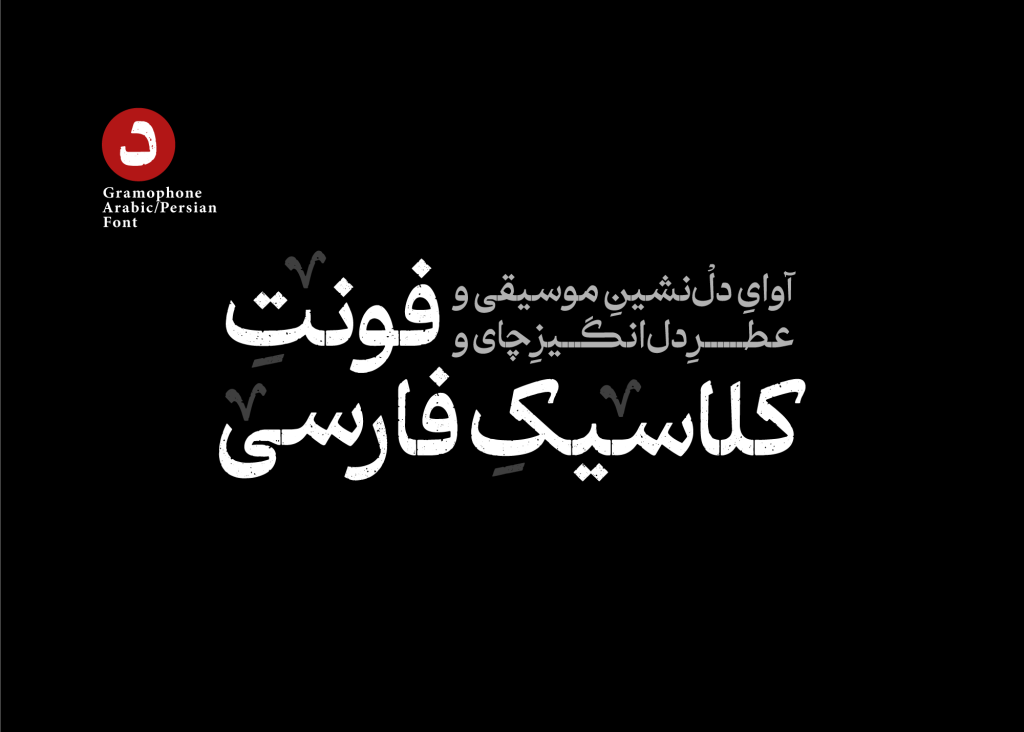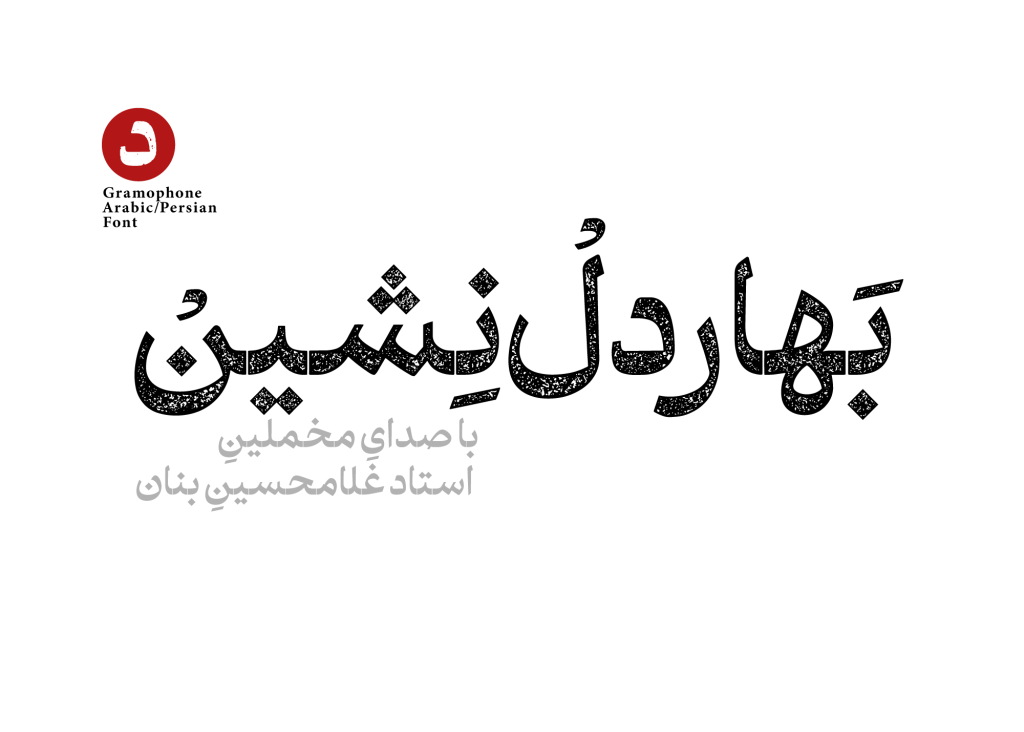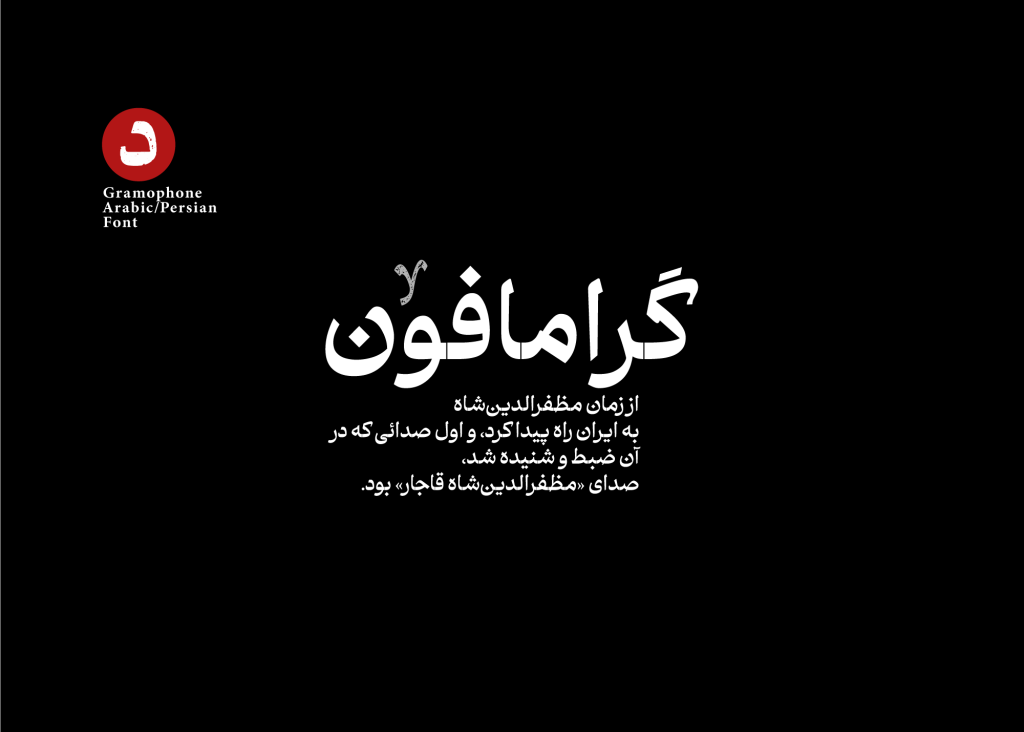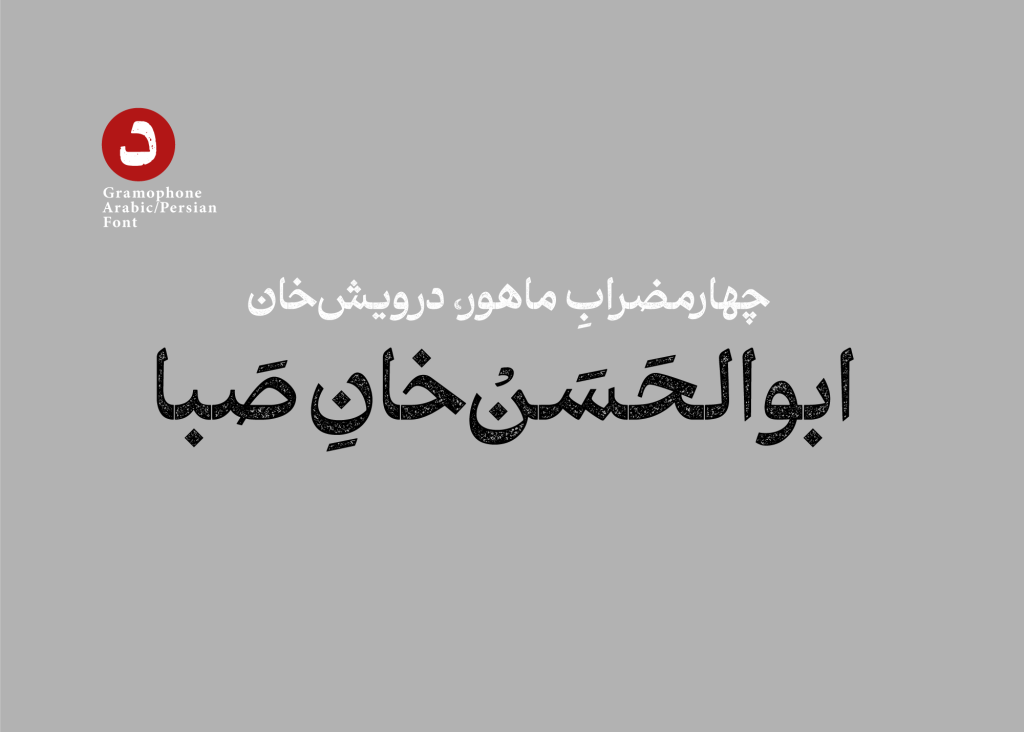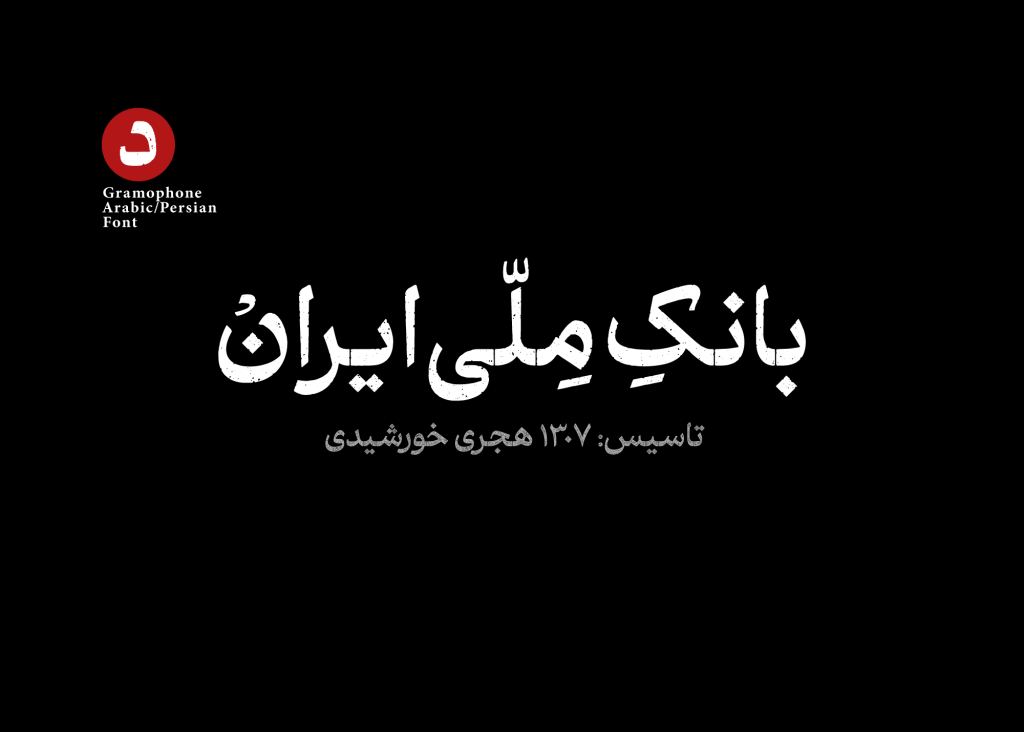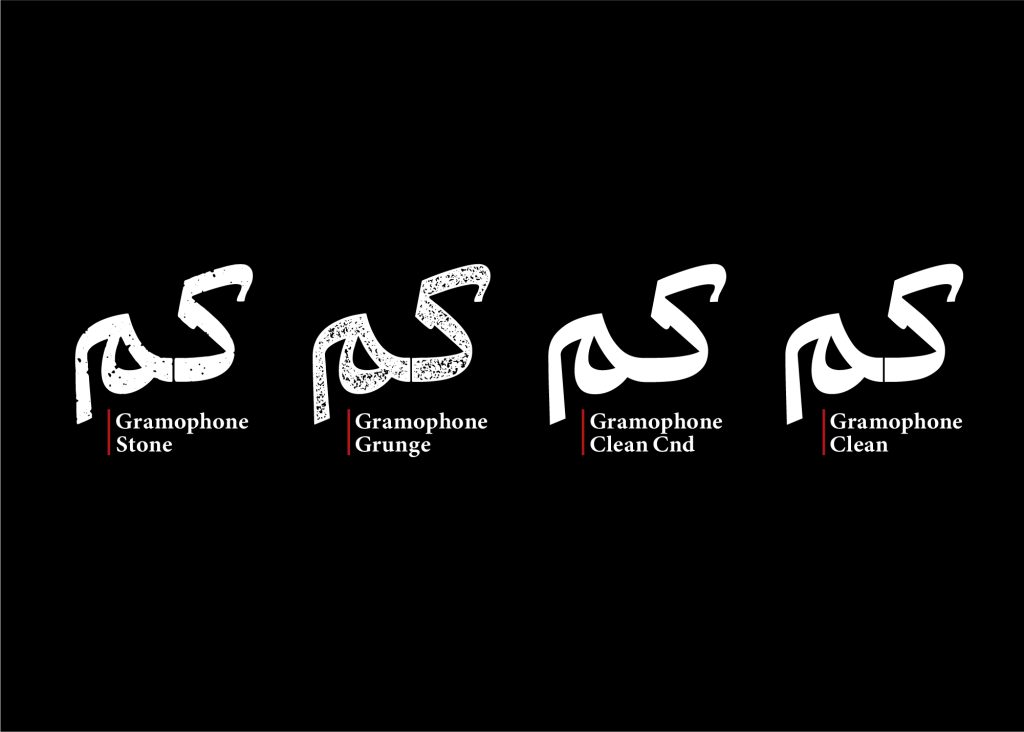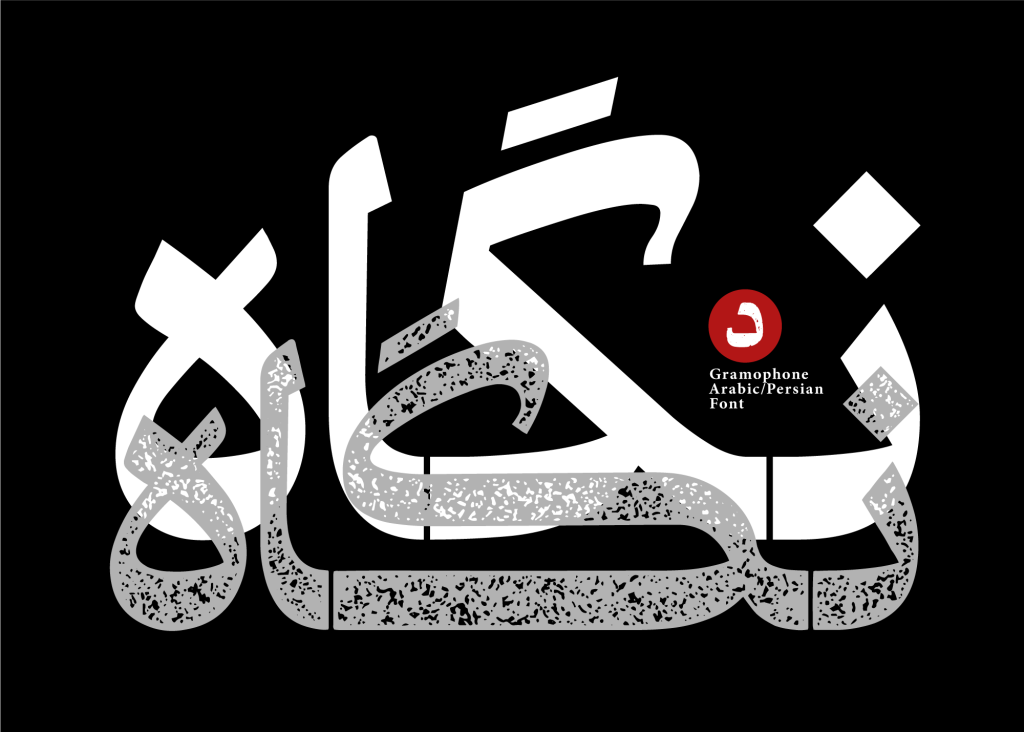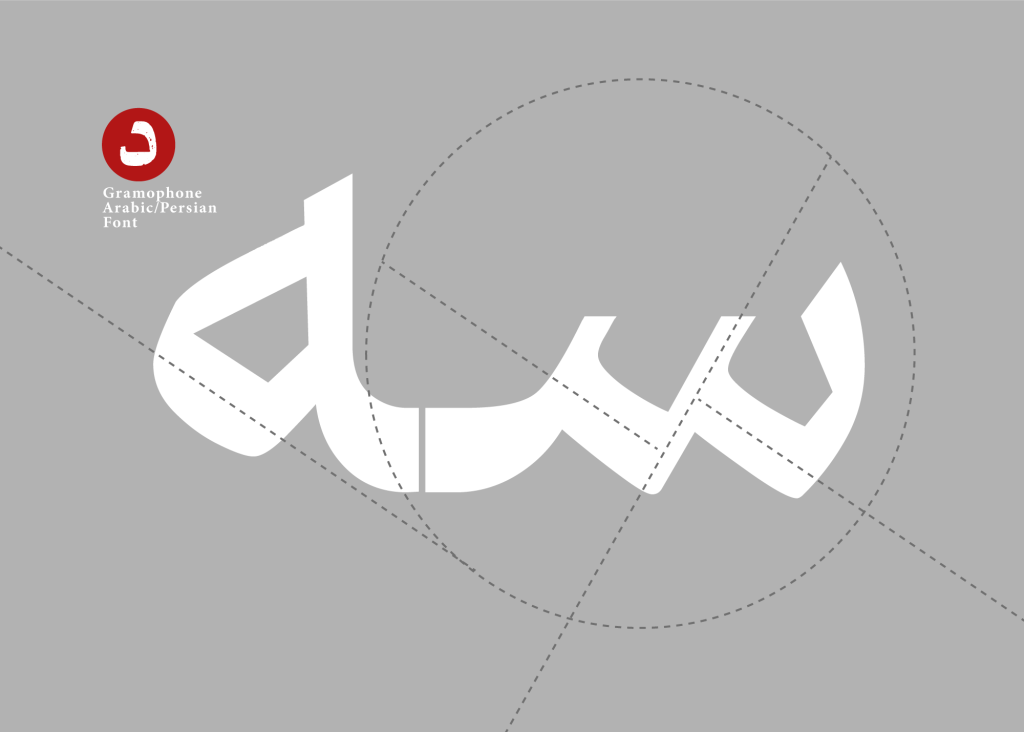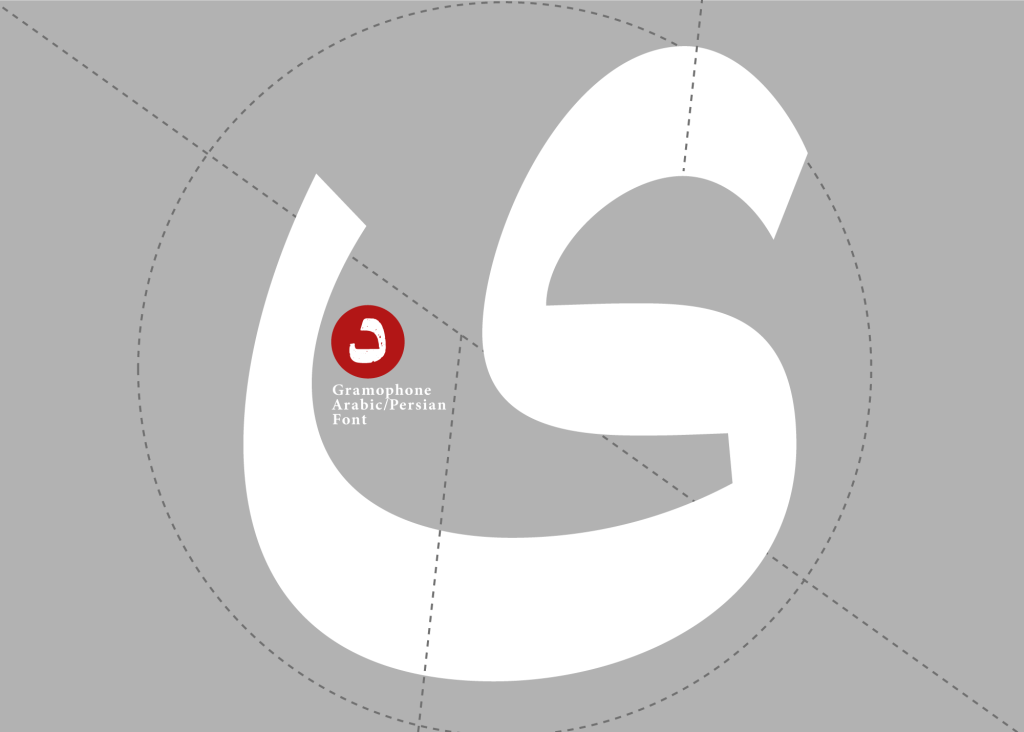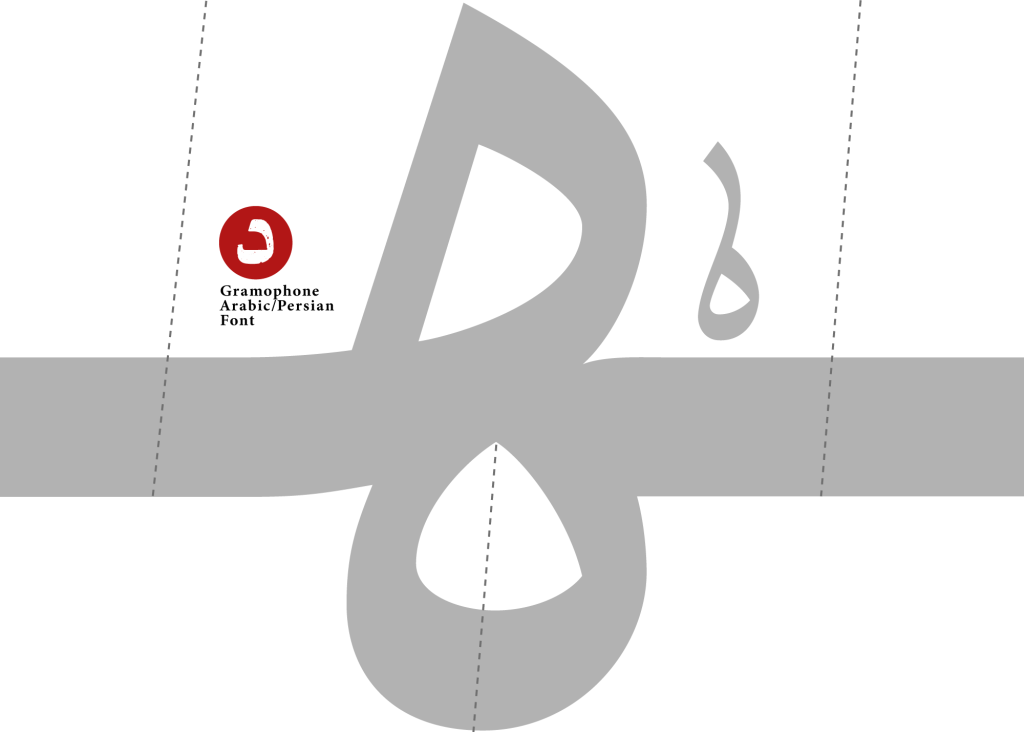
فونت گرامافون – قلمی نوستالژیک با استاندارد های امروزی
فونت گرامافون قلمی که زیر نظر طراح آن آقای کریم عامری ایجاد و ابداع گردیده است. یکی از اهداف در طراحی این گرامافون شکل گیری قلمی با حس و حال قدیمی و نوستالژیک در عین دارا بودن استاندارد های امروزی و نو می باشد.
این قلم حاصل همنشینیِ متناسبِ فرمهایی کمتر استفاده شده از خانواده خط نسخ است که در مواردی از خط ثلث نیز الهام گرفته شده است. منابع ایدهبرداریِ از شکل گیری فضا و سبک ایجاد این قلم ، برخی از کتابها، کتیبهها و تابلوهای قدیمی بوده است.
به جهت زنده نگاه داشتن فضا و اتمسفر نوستالژیک و قدیمی این تایپ فیس و فراموش نشدن ساختار گذشتگی آن، حروف گرامافون به صورت تقطیع شده در کنار هم قرار گرفته تا یادآور شیوهی چاپ سربی باشد؛ و همچنین علاوه بر سبکِ «تمیز» و «تمیز متصل»، دو سبکِ «چرک» و «سنگی» به بستهی این محصول اضافه گردیده است.
گرامافون و سبک های مختلف آن
تفاوت سبکهای «چرک» و «سنگی» علاوه بر جنس بافتها در «تخریبی» یا «غیرتخریبی» بودن خطهای تشکیلدهندهی فرمهاست. به این معنا که سبک چرک دارای یک بافت سنگین در وسط حروف است، اما در بافت سنگی، خطهای دور حروف نیز تخریب شدهاند.
از دیگر تلاش ها و تمرکز های وافر و شدید در طراحی این قلم دوری کردن از ایجاد پیچیدگی های فرمی و در نقطه مقابل آن تلاش برای ترسیم سطح و دورهای کاملاً صاف و هموار در دور های کناری است.
گرامافون دارای شخصیتی با صلابت و فضای رسمی و قدیمی را در دل خود دارد. مناسب برای عناوین و متون با حس رسمی و قدیمی می باشد در زیر تصاویری نمونه از این قلم را مشاهده می کنید.